20 font keren dan terbaik untuk website Anda
Pada artikel ini, kami akan memberikan daftar 20 font untuk website (font HTML) yang dapat diinstal pada situs Anda. Dengan menggunakan font yang kami rekomendasikan, desain situs Anda dapat ditingkatkan, dan konten Anda menjadi lebih mudah dibaca.
Seberapa Pentingkah Font HTML?
Disadari atau tidak, font HTML memiliki peran penting untuk website Anda. Memilih desain font untuk website yang tepat dapat meningkatkan sisi estetika halaman website yang dimiliki dan dapat mempermudah pengunjung untuk membaca konten Anda.
Namun jika Anda memilih font apapun tanpa alasan yang jelas, bersiaplah untuk mendapatkan konsekuensi buruk yang dapat memengaruhi penampilan website dan konten Anda.
Terlebih, font dapat memengaruhi performa website secara negatif maupun positif. Semuanya bergantung pada pilihan font website Anda, apakah font nya web-safe atau tidak. Kami akan membahasnya lebih lanjut, maka dari itu, teruslah membaca.
Bagaimana Cara Mengganti Font melalui HTML Code?
Untuk mengganti font melalui HTML, Anda dapat menggunakan style attribute dengan tag pendefinisian paragraf <p>. Inilah contohnya:
<p style = "font-family:courier,arial,helvetica;"> Write your text here </p>
Ada tiga tipe font utama pada contoh ini yaitu Courier, Arial, dan Helvetica. Arial dan Helvetica merupakan backup jika Courier tidak ditemukan atau corrupted.
Apa itu “Web Safe Font”?
Istilah ini mendeskripsikan font yang terinstall secara universal di berbagai perangkat. Dengan web safe font, seharusnya website dapat dimuat secara cepat karena font-font tersebut disimpan secara lokal.
Kecepatan memuat halaman harus diperhitungkan karena hal tersebut juga memberi efek pada SEO dan memengaruhi ranking pada SERP.
Itulah mengapa, menggunakan web safe font sangat direkomendasikan agar pembaca Anda dapat melihat konten dengan mudah dan performa website dapat berjalan dengan baik.
Perlu Anda ingat bahwa ada beberapa alternatif web safe font, yang biasanya memiliki karakteristik yang sama seperti typefaces populer. Sebagai contoh, font Sans Serif seperti Helvetica adalah Acumin dan Univers.
Namun tidak seperti web-safe yang lain, font alternatif biasanya tidak didapatkan secara prepakaged pada semua OS. Mungkin Anda ingin menggunakan salah satu diantara font alternatif tersebut karena font yang populer sudah terlalu banyak digunakan. Tapi, perlu diingat bahwa Anda dapat mengorbankan kecepatan website.
Apa itu Five Font Families?
Dalam tipografi, tiap font memiliki keluarga besarnya yang mana masing-masing berjumlah lima. Font tersebut dikategorikan berdasar kemiripan desainnya. Mereka adalah:
Cursive (contoh: Zapf-Chancery)
Font pada Cursive family meniru tulisan manusia dan biasanya huruf-huruf dari font ini bersambungan seperti mengalir. Banyak yang mengasosiasikan font Cursive dengan menulis cepat dan kaligrafi.
Fantasy (contoh: Star Wars)
Font Fantasy biasanya memiliki elemen dekoratif pada setiap hurufnya, tetapi masih merepresentasikan karakter dari font tersebut. Banyak buku fiksi atau film yang menggunakan typefaces dari rangkaian font ini untuk judul demi mempertegas efek dari konten tersebut.
Serif (contoh: Times New Roman)
Fitur yang paling menonjol dari font family satu ini adalah garis kecil pada akhir tiap akhiran garis yang besar pada huruf atau simbol pada font family ini. Mereka menciptakan nuansa formal dan elegan. Berbagai website biasanya menggunakan font Serif untuk teks pada body.
Sans-serif (contoh: Helvetica)
Berbeda dengan Serif, Sans-serif tidak memiliki garis kecil yang menempel pada tiap hurufnya. Dan, kebanyakan, font dari font family ini biasanya memiliki lebar garis yang mirip. Desain tersebut membuat font family ini terkesan modern dan minimalis.
Monospace (contoh: Courier)
Tiap huruf dan simbol dari font Monospace memiliki spasi horizontal yang sama persis. Karena font nya konsisten dan mudah dibedakan, font-font ini biasanya digunakan oleh typewriter dan terminal komputer.
Font Apa yang Harus digunakan untuk Website?
Web-safe font sangat direkomendasikan untuk website Anda karena alasan kompatibilitas untuk berbagai perangkat.
Yang terutama adalah, pilih font yang sesuai dengan gaya website dan tone menulis Anda. Bila font tersebut selaras dengan gaya website dan gaya menulis, maka Anda akan terlihat lebih profesional. Selain itu, hal ini juga dapatmeningkatkan pengalaman membaca pengunjung web Anda.
Kabar baiknya adalah Anda dapat menemukan font yang sangat sesuai dengan website Anda dengan mudah pada jajaran rekomendasi font untuk website di bawah ini!
Font Terbaik Untuk Website
Semua daftar font yang kami berikan merupakan web-safe font, jadi Anda tidak perlu khawatir akan kompatibilitas atau performanya. Mari kita ulas 20 font terbaik untuk font HTML:
1. Arial
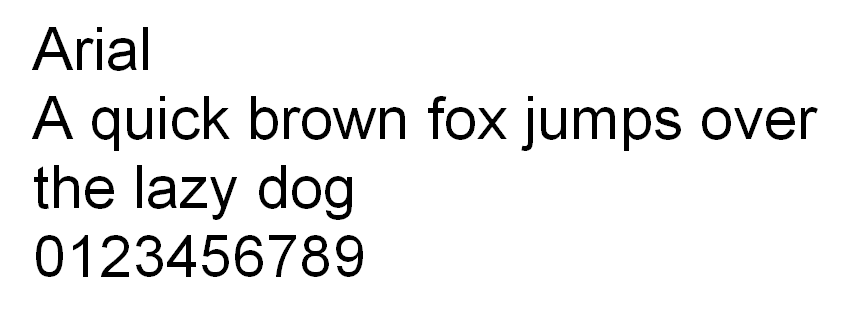
Arial merupakan font yang paling banyak digunakan untuk media online maupun cetak. Terlebih lagi, font ini merupakan font default Google Docs yang merupakan office suite populer milik Google. Banyak kritikus mengatakan bahwa font member sans-serif ini sesuai untuk digunakan di berbagai hal.
2. Times New Roman
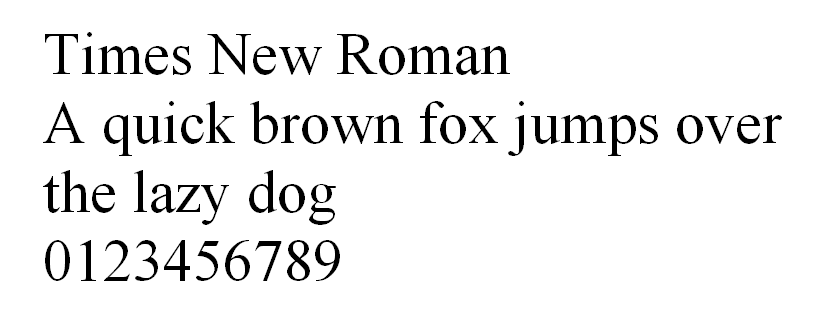
Times New Roman merupakan variasi font lama dari Times yang juga berasal dari grup Serif. Dengan tampilan yang profesional, font ini menjadi pilihan favorit media cetak dan konten yang lebih formal. Ditambah lagi, typeface ini dipilih oleh berbagai situs berita dan institusi lainnya.
3. Helvetica
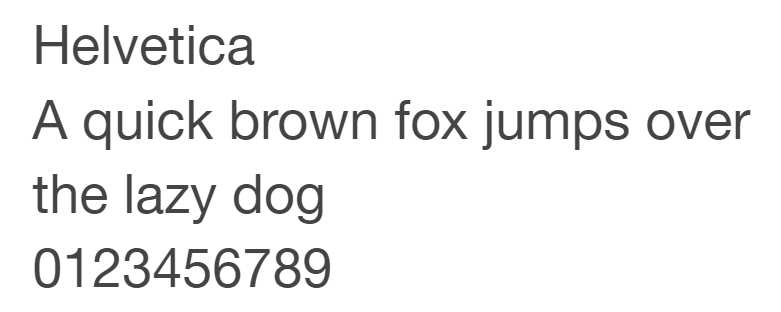
Para desainer mencintai Helvetica karena kenetralannya dan cocok untuk berbagai jenis bisnis. Itulah mengapa banyak merek terkenal seperti Jeep, Kawasaki, Motorola, dan BMW memilih font ini. Maka dari itu, font ini dirasa cocok untuk digunakan dengan berbagai tujuan.
4. Times
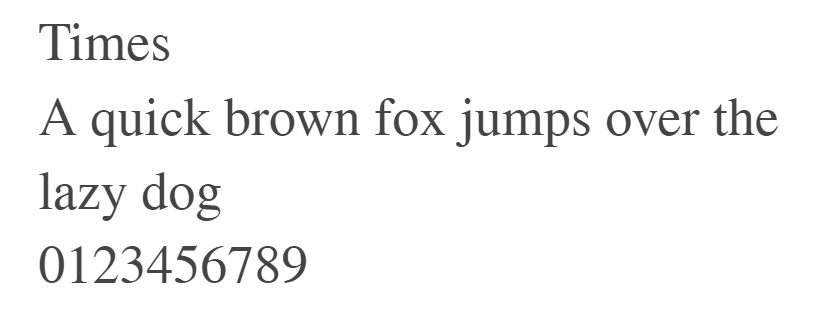
Pada umumnya, font ini banyak digunakan oleh media cetak seperti koran, dan lekat hubungannya dengan jurnalisme maupun tulisan akademis. Maka dari itu, jika Anda ingin menambah nuansa tradisional sekaligus formal pada website Anda, gunakan lah font ini.
5. Courier New
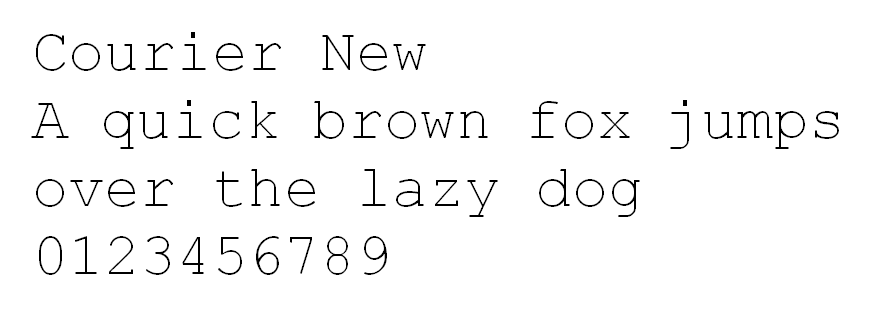
Font ini merupakan alternatif dari font Courier. Font ini lebih ramping dan lebih enak dipandang pada layar Anda. Karena alasan tersebut, awalnya, perangkat elektronik menggunakan Courier New. Tapi karena font ini juga merupakan font typewriter, Courier New akan tampak bagus pada website yang membutuhkan desain old-school.
6. Verdana
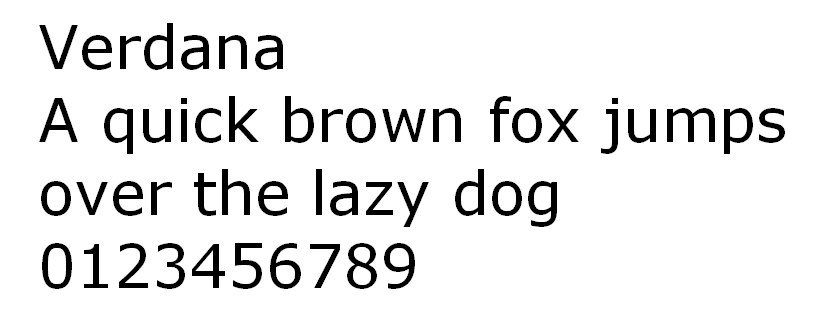
Typeface ini mudah dibaca walaupun ukuran font nya kecil, atau bahkan ketika ditampilkan pada layar dengan resolusi kecil. Hal tersebut membuat Verdana menjadi primadona font untuk layar. IKEA adalah salah satu perusahaan yang menggunakan font ini. IKEA tidak hanya menggunakan Verdana pada situs mereka, tapi juga katalog cetaknya. Jika ANda mencari font HTML dengan tingkat readability tinggi, Anda dapat mencoba typeface ini.
7. Courier
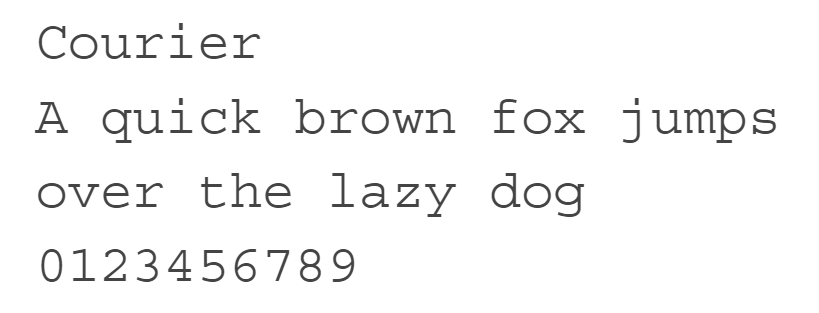
Anda dapat menganggap bahwa Courier merupakan font yang terkenal pada keluarga monospace. Terlebih, semua sistem operasi memiliki font ini secara prepackaged. Font HTML ini merupakan standar untuk layar lebar. Maka dari itu, jika website Anda memuat tentang dunia perfilman, Anda dapat mempertimbangkan font ini.
8. Arial Narrow
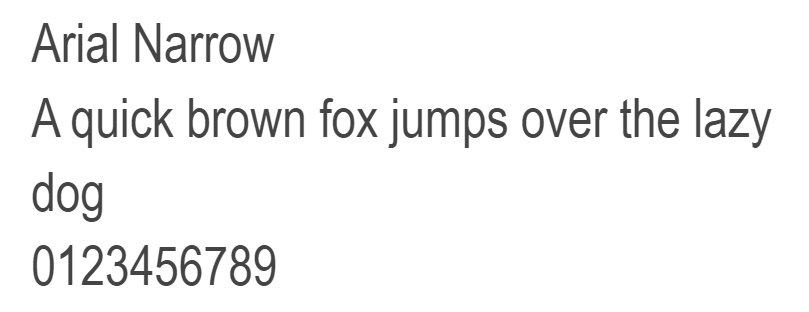
Font ini merupakan versi lain dari Arial yang memiliki tampilan lebih halus daripada Arial. Opsi alternatif ini juga bisa Anda temukan pada berbagai OS. Arial Narrow juga masih mempertahankan karakteristik pendahulunya yang serbaguna dan sesuai untuk halaman web apapun.
9. Candara
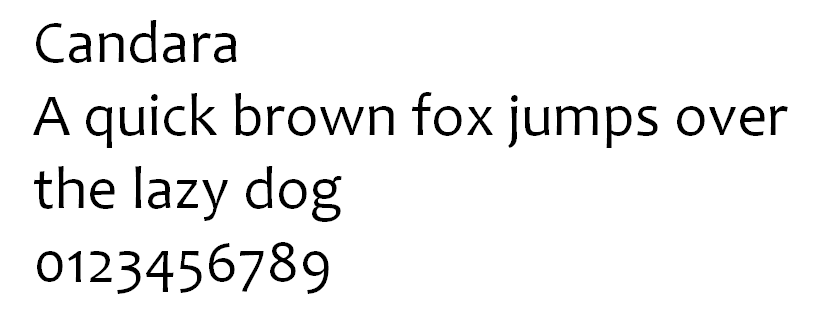
Microsoft VIsta merupakan OS pertama yang memperkenalkan Candara ke khalayak umum. Font ini mendukung sistem rendering teks Windows ClearType, yang meningkatkan readability teks pada layar LCD.
10. Geneva
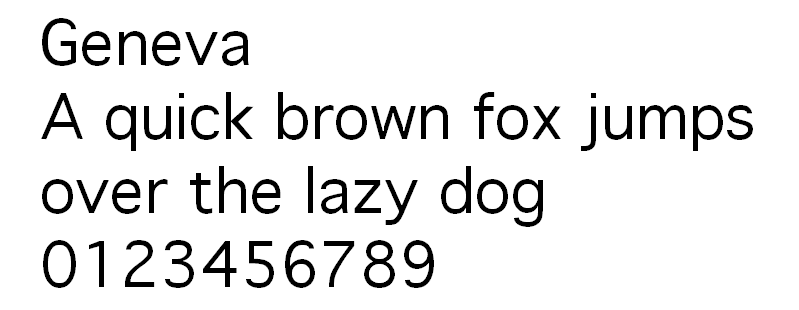
Geneva termasuk pada grup Sans-serif. Font ini aslinya dikembangkan oleh Apple. Seperti typeface lainnya pada font family ini, Geneva memberi tampilan yang bersih dan modern pada website atau blog Anda.
11. Calibri
Calibri adalah font default Microsoft Office. Sebagaimana Microsoft Windows masih berada di puncak tren pangsa pasar OS desktop, user seharusnya tidak memiliki masalah ketika membaca font HTML ini pada browser mereka.
12. Optima
Font Optima terinspirasi dari huruf-huruf Roman Capital. Tipe ini juga digunakan untuk berbagai hal, dari marka jalan hingga logo produk kecantikan. Font HTML ini elegan dan mudah dibaca, yang mana membuat konten Anda menjadi lebih menonjol.
13. Cambria
Calibri, Candara dan Cambria termasuk dalam font ClearType yang dibuat oleh Microsoft. Dengan proporsi yang pas, Cambria didesain untuk experience membaca on-screen bahkan ketika harus ditampilkan dalam ukuran kecil.
14. Garamond
Garamond adalah tipe font klasik yang sesuai untuk berbagai buku cetak. Desainer buku menganggap font ini sebagai salah satu opsi terbaik untuk digunakan pada buku cetak karena halus dan mudah dibaca. Font ini juga dapat memberikan nuansa antik pada website atau blog Anda.
15. Perpetua
Font ini lahir dari buah pemikiran seorang pemahat Inggris yang terinspirasi dari monumen dan memorial lettering. Karakteristik font yang formal membuat Penguin Classics dan University of Pennsylvania menggunakan Perpetua untuk publikasinya. Intinya, halaman edukatif dan informatif dapat merasakan keuntungan dari font HTML ini.
16. Monaco
Monaco dapat Anda temukan di MacOS. Font ini termasuk dalam monospace family, yang digunakan pada Terminal dan Xcode. Font ini memiliki desain yang unik, yang membuat Anda dapat membedakan huruf-huruf yang mirip. Gunakan font ini untuk website yang bertemakan koding dan website yang ingin memudahkan pembacanya untuk membedakan tiap hurufnya.
17. Didot
Menurut berbagai pakar, Didot merupakan font serif neoclassical, yang mana font ini memiliki desain klasik dengan sedikit sentuhan modern. Font ini digunakan oleh CBS News dan The Late Show With Stephen Colbert. Typeface ini terkenal akan kontrasnya yang tinggi.
18. Brush Script MT
Font ini mengadopsi gaya kaligrafi teknik tulis tangan. Hal tersebut membuat Brush Script MT menjadi font HTML yang cantik sekaligus mudah dibaca. Walaupun Brush Script MT elegan dan sedikit meriah, font ini sesuai untuk catatan editorial dan sejenisnya.
19. Lucida Bright
Lucida Bright adalah salah satu versi dari Lucida. Namun, font ini lebih kontras dari pendahulunya. Terlebih, font ini lebih ramping, sehingga tepat digunakan untuk buku panduan atau majalah karena hemat tempat. Scientific American Magazine merupakan salah satu lembaga yang menggunakan typeface ini.
20. Copperplate
Perancang font Copperplate sejatinya menginginkan font ini untuk digunakan hanya pada header atau judul. Jadi, font ini hanya berisi huruf kapital. Typeface ini menjadi terkenal setelah Who Wants To Be A Millionaire membuat font ini sebagai ciri khasnya.
Maaf, Tidak Direkomendasikan (Comic Sans)
Seluruh internet user memiliki dasar pemikiran yang sama: tidak menyukai font Comic Sans. Orang-orang menganggap bahwa font ini kekanakan, dan tidak cocok digunakan secara profesional.
Bertahun-tahun font ini menjadi bahan meme. Maka dari itu, kami tidak merekomendasikannya. Meskipun Comic Sans adalah font yang aman untuk web, masih ada banyak opsi yang akan membuat situs Anda terlihat jauh lebih baik daripada Comic Sans.
Kesimpulan
Kami telah mengulas 20 font HTML terbaik yang dapat digunakan untuk website Anda. Setelah Anda mengetahui karakteristik dan kegunaannya, sekarang saatnya memutuskan untuk memilih font yang paling sesuai dengan gaya dan tone situs Anda. Sampai jumpa di artikel berikutnya!